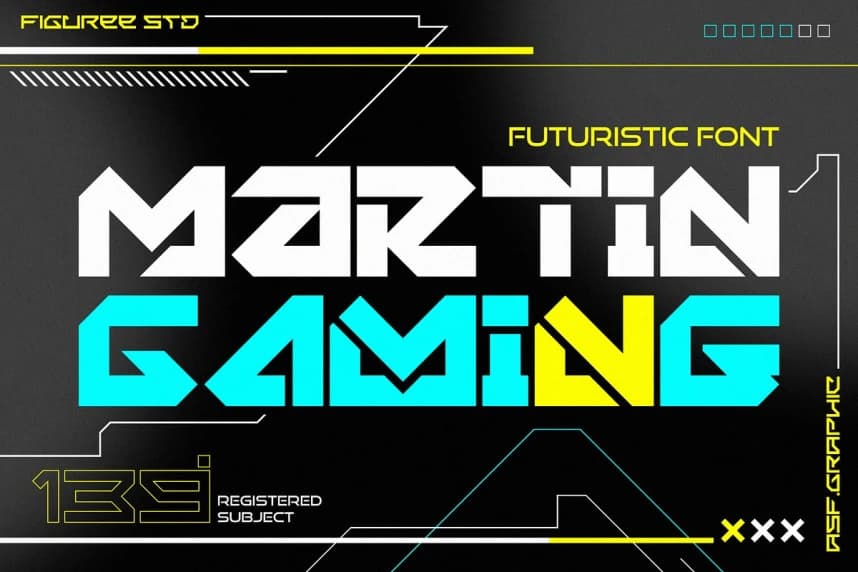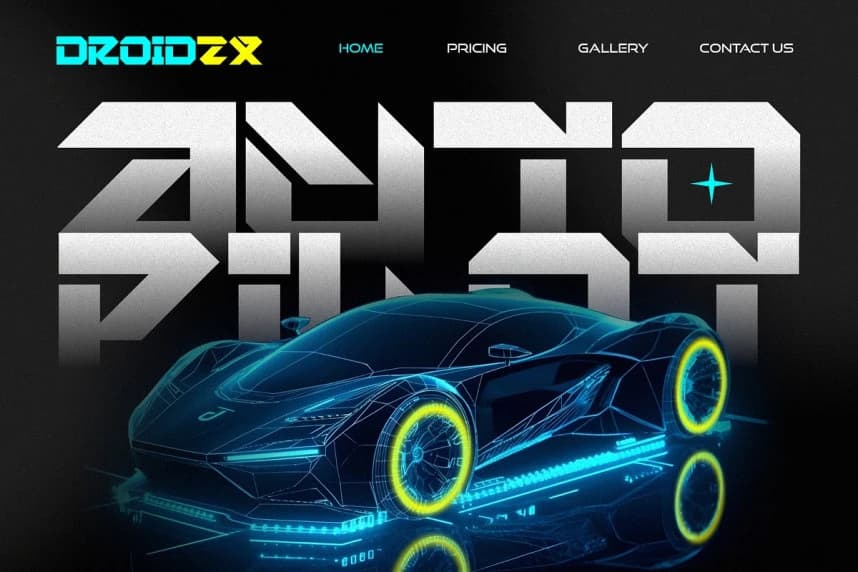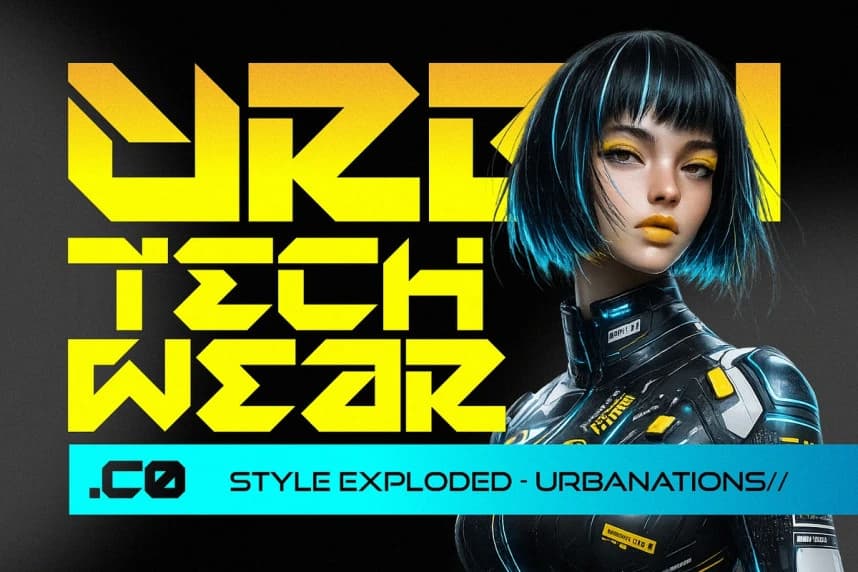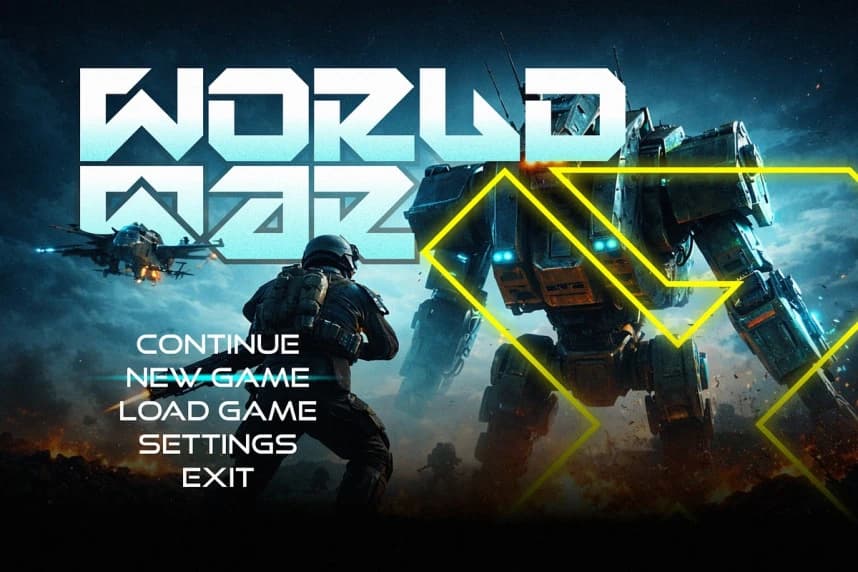
Martin Gaming Font
Martin Gaming Font – Futuristic Techno Font, modern yaratıcı projeler için keskin, dijital odaklı bir görünüm sunmak üzere tasarlanmıştır. Teknolojiye ilham veren bir yapıya sahip olan bu yazı tipi, oyun arayüzleri, bilim kurgu başlıkları, teknoloji görselleri ve yüksek etkili dijital düzenler için
Martin Gaming Font – Futuristic Techno Font, modern yaratıcı projeler için keskin, dijital odaklı bir görünüm sunmak üzere tasarlanmıştır. Teknolojiye ilham veren bir yapıya sahip olan bu yazı tipi, oyun arayüzleri, bilim kurgu başlıkları, teknoloji görselleri ve yüksek etkiye sahip dijital düzenler için idealdir.